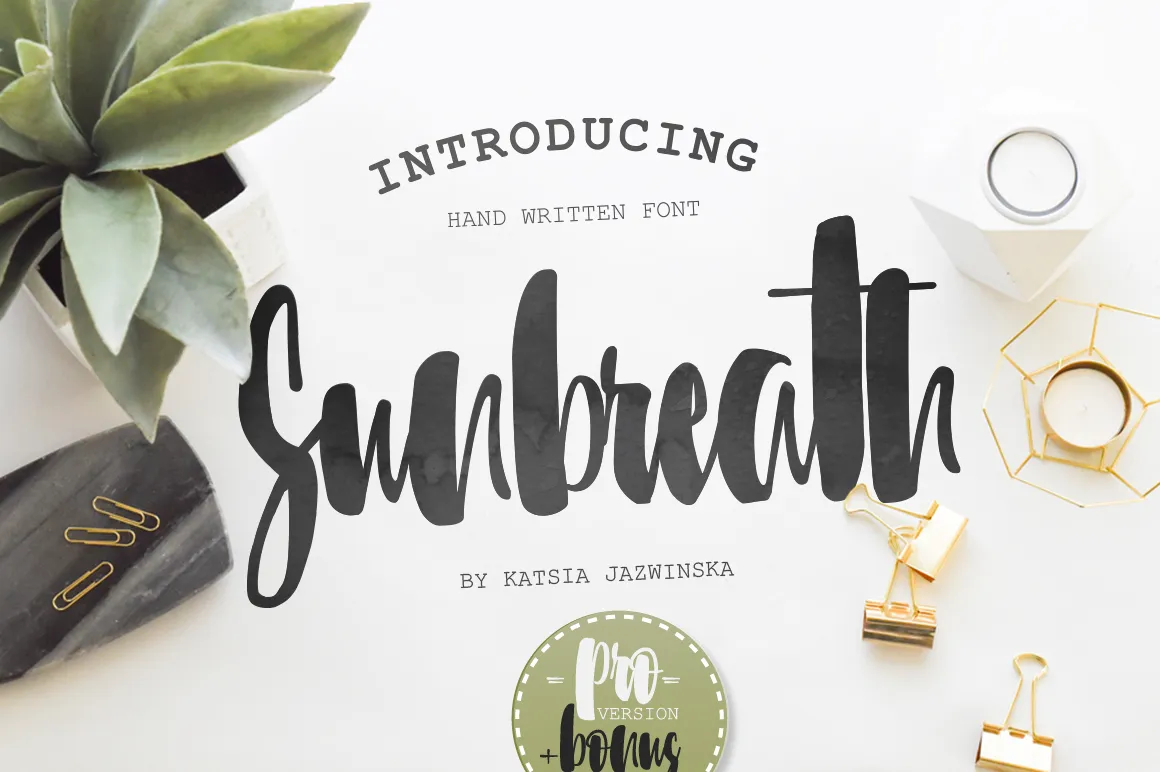
A Sunbreath é uma fonte à mão livre desenhada com uma ferramenta apropriada que destaca sua força e definição nos traços. Suas linhas robustas e decisivas transmitem um forte sentimento de confiança, indicando claramente estar pronto para fazer o trabalho. Essa fonte é ideal tanto para projetos pessoais como comerciais individuais com a licença padrão. Para aplicações onde você pretende vender itens ou usar essa fonte em grande escala, será necessário adquirir uma licença Extended License. A Sunbreath é perfeita para quem busca um visual poderoso e definido sem comprometer o uso comercial de sua criação.